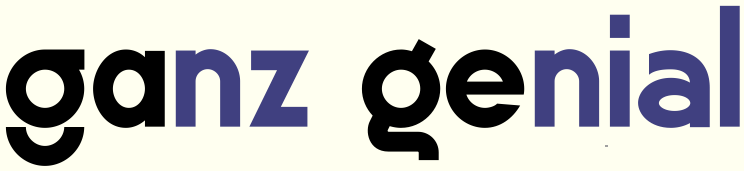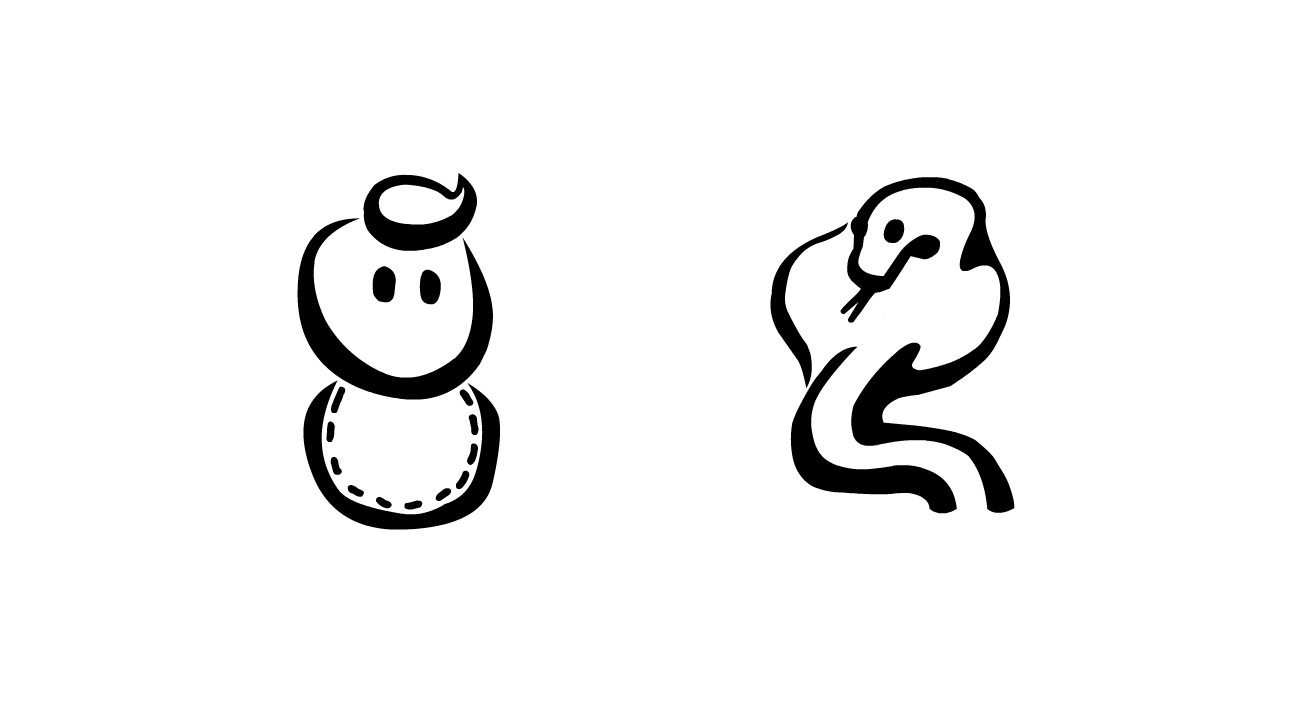
Und wie nennt man solche g?
Ich habe da gerade eine neue Schrift in Arbeit, die über Stylesets verschiedene g bekommt. Nachdem wir ja schon über Elefanten und Brillen-g gesprochen haben, wie würdet ihr solche nennen...
Ich finde das zweite sieht aus wie eine Schlange, die sich beim Flötenspiel aus ihrem Körbchen erhebt. ;-) Das erste hat was von Küken, wenn man im Tierreich bleiben möchte. :-?
Wenn man nicht im Tierreich bleiben will, hat das linke ein Lätzchen (oder einen Kragen) und das rechte hat eine Monokelform.
Ich musste bei dem rechten G an eine Kaulquappe oder ein Spermium denken. Das linke ist für mich "denkend".